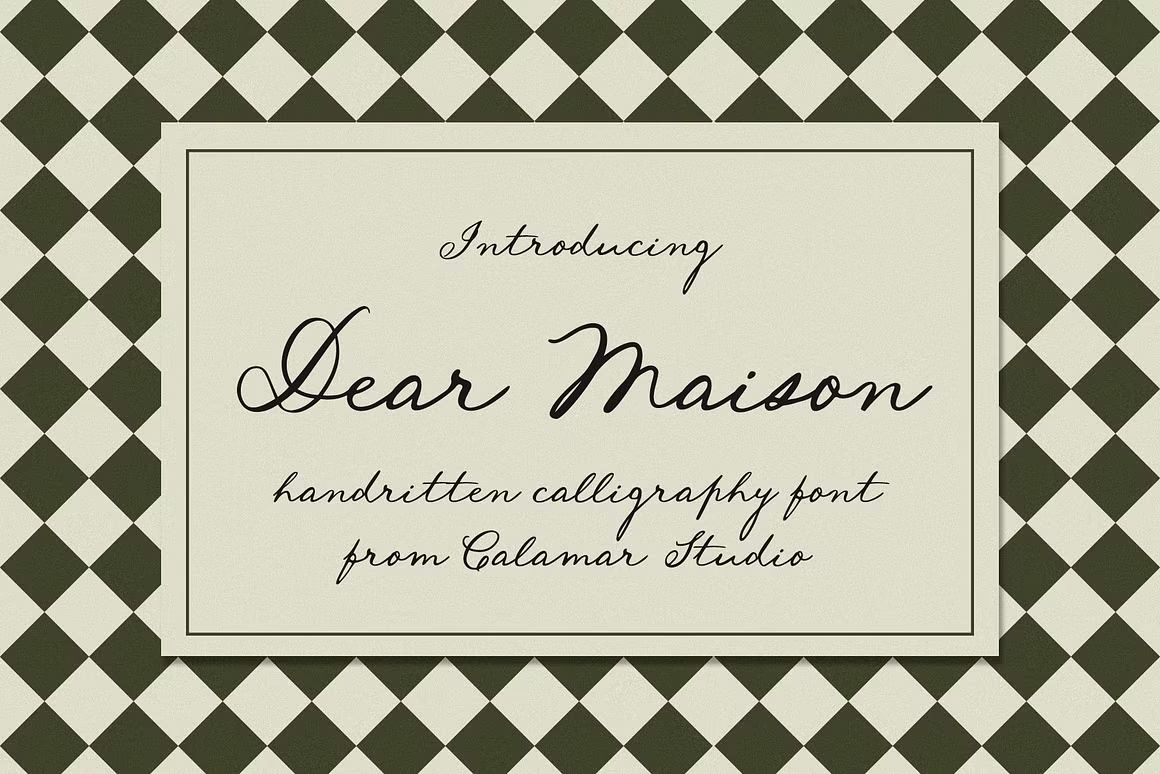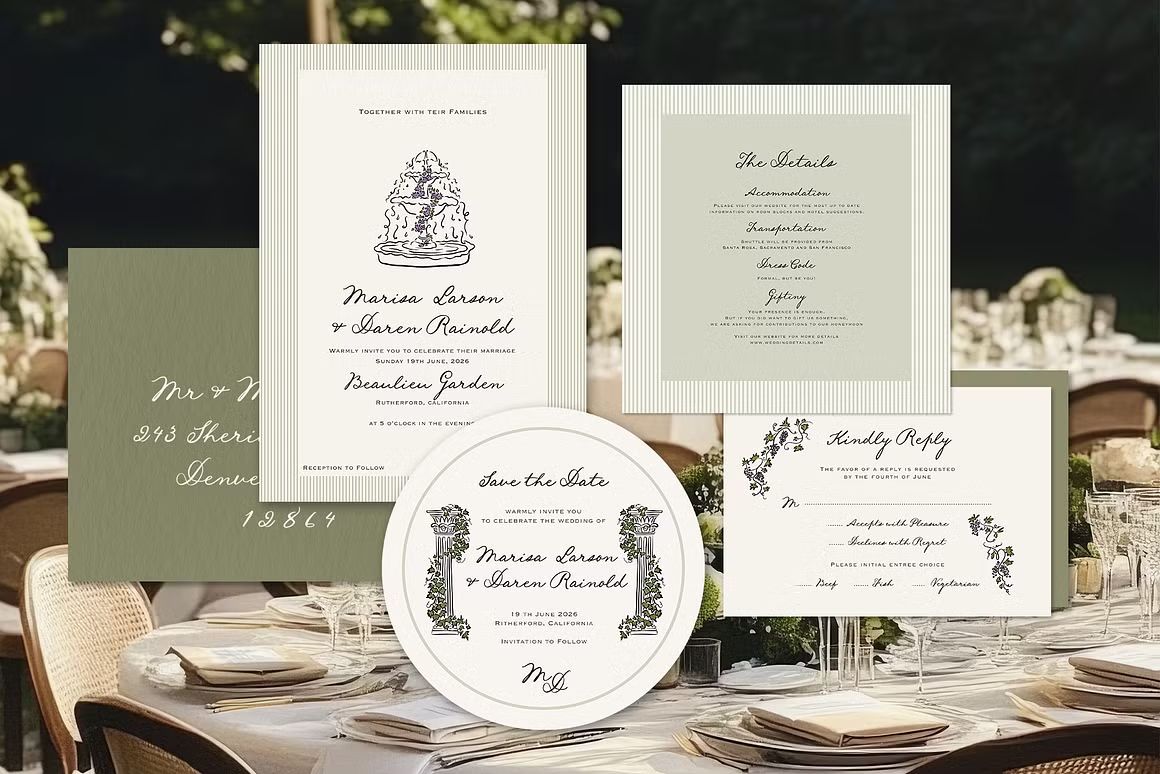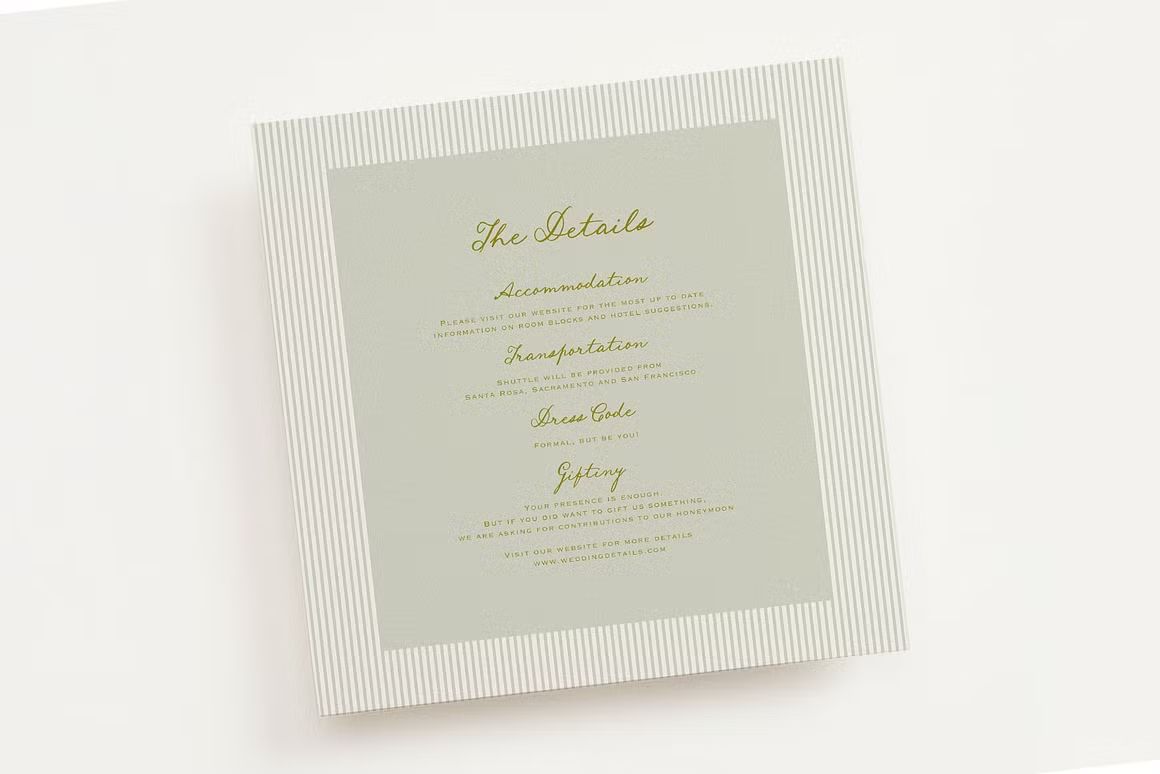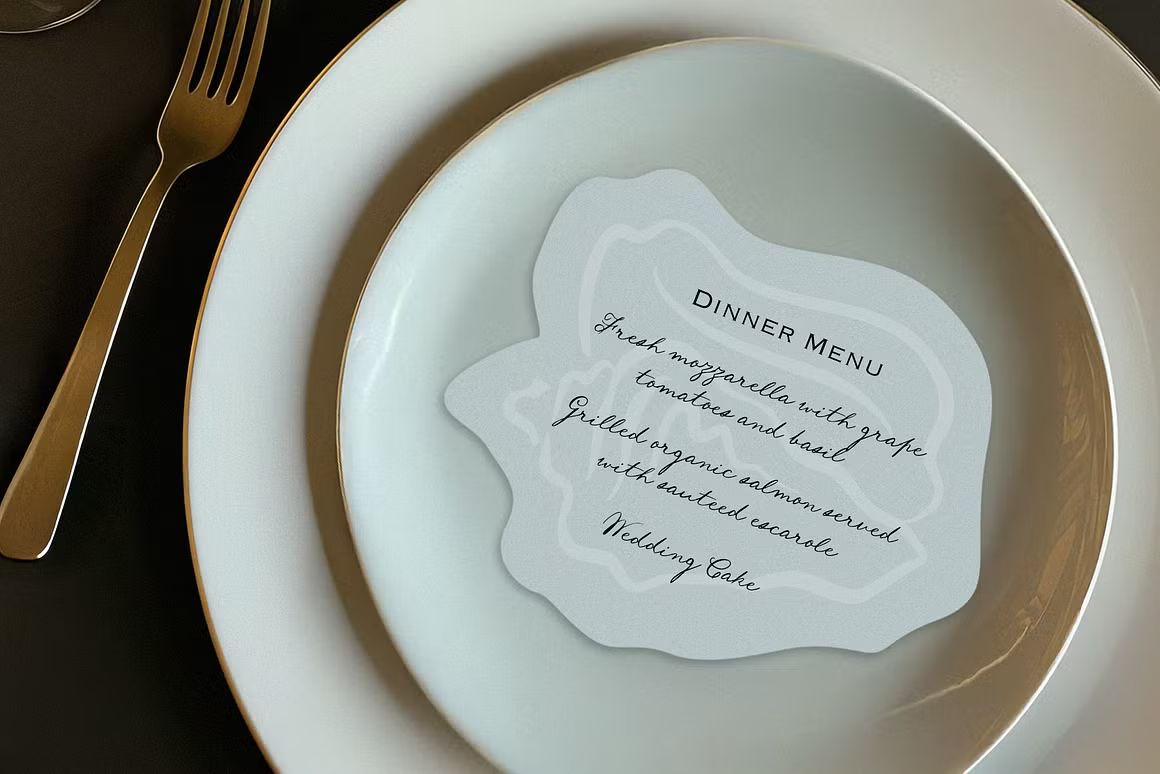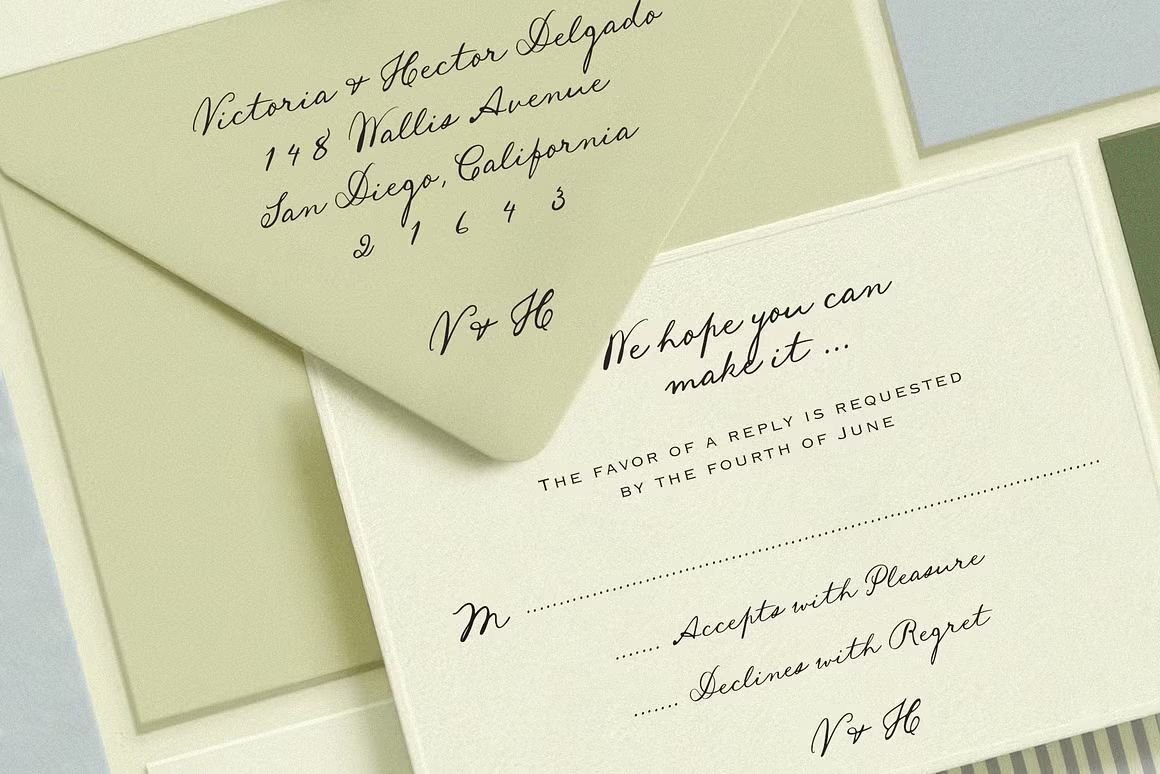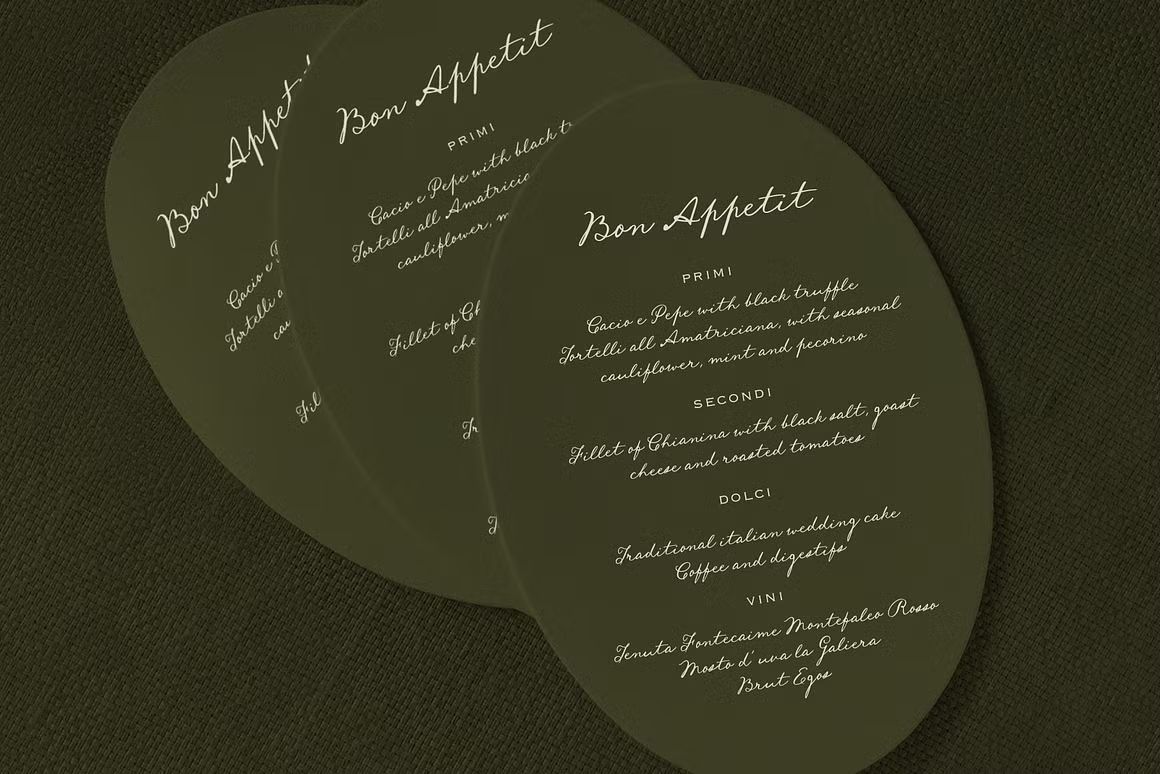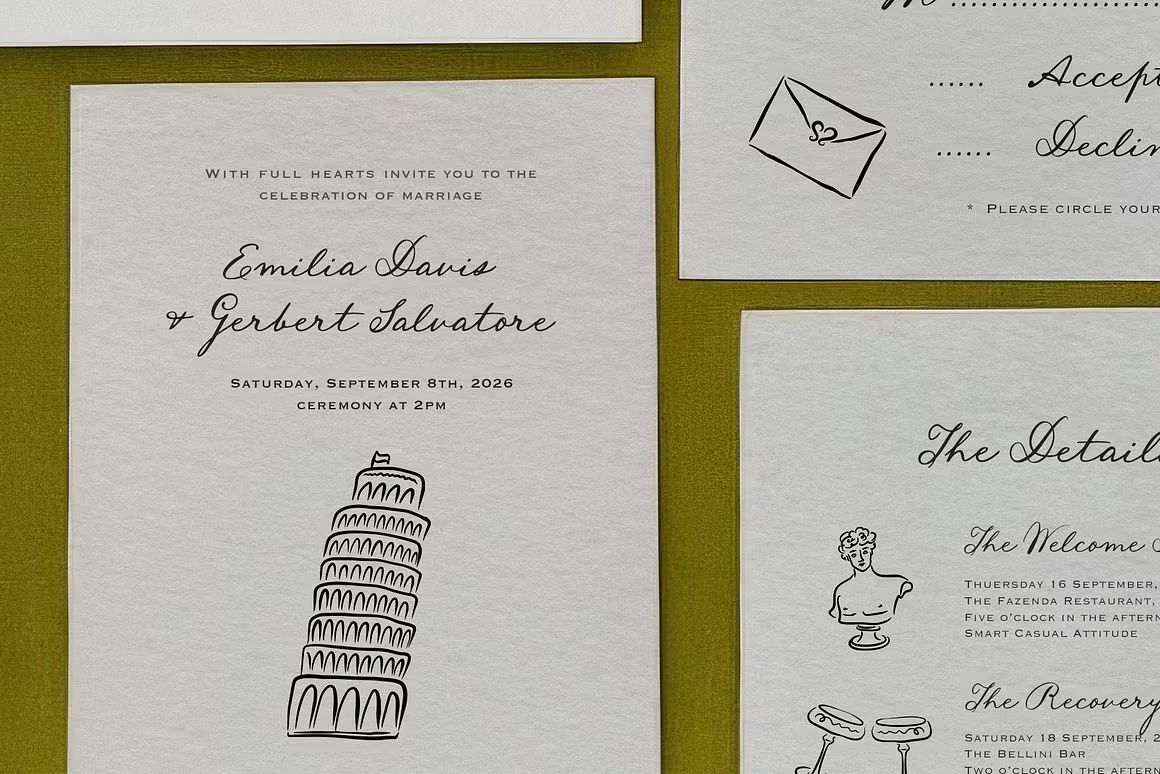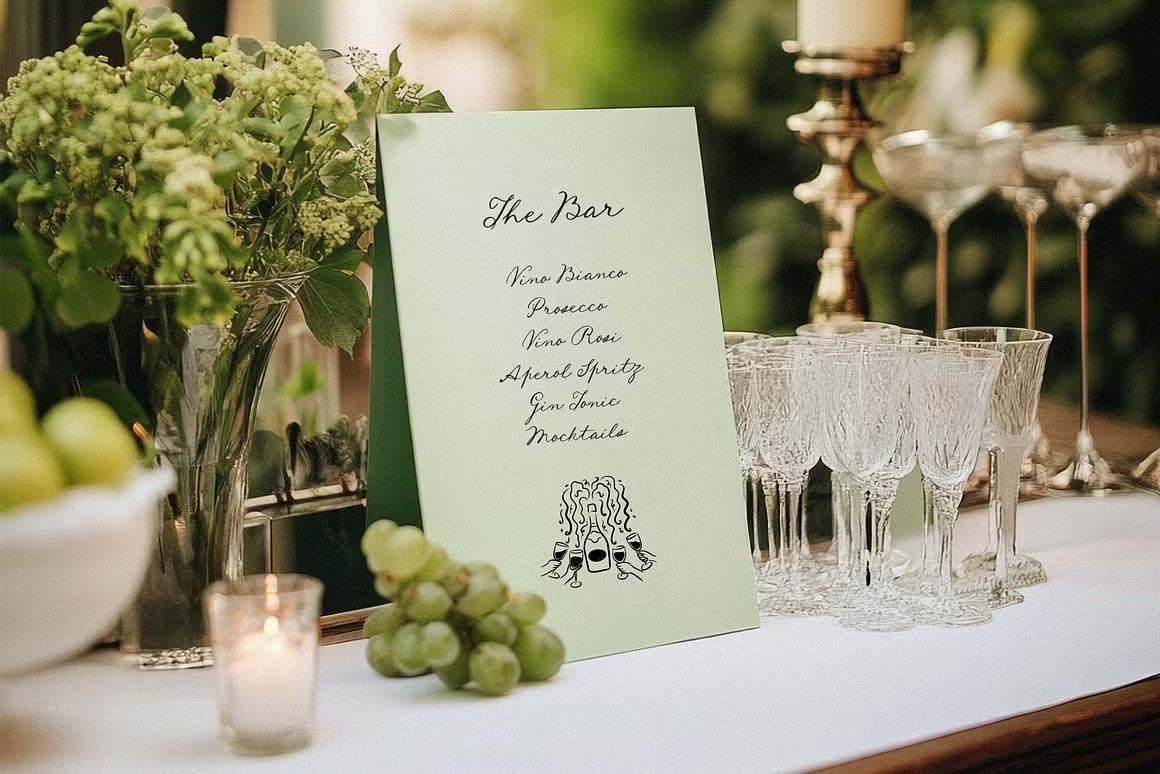
Dear Maison – Handwritten Font
Dear Maison adalah font handwritten dengan gaya elegan dan natural, cocok untuk desain branding, undangan, logo, dan proyek kreatif yang menginginkan sentuhan personal dan halus.
Dear Maison adalah font handwritten yang menghadirkan nuansa lembut, elegan, dan personal. Dengan garis yang halus dan bentuk huruf yang mengalir alami, font ini cocok digunakan untuk berbagai proyek desain seperti undangan pernikahan, logo, kemasan produk, branding, dan media sosial. Gaya tulis tangan yang modern ini memberikan kesan eksklusif dan hangat dalam setiap tampilan.
Fitur unggulan:
• Gaya tulisan tangan yang elegan dan natural
• Cocok untuk wedding, logo, branding, dan desain feminin
• Huruf besar, huruf kecil, angka, dan simbol lengkap
• Ideal untuk proyek cetak maupun digital